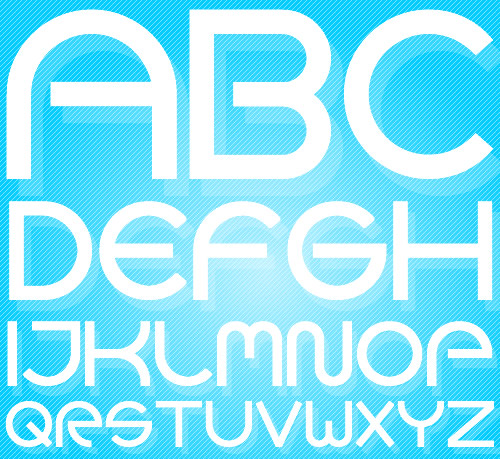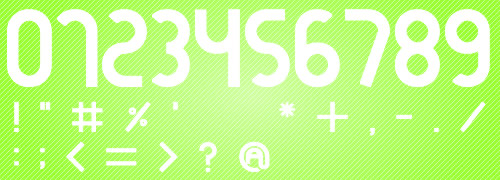
Font Design: Goca Logotype Beta
Il Font Design di oggi è: Goca Logotype Beta (download)
Questo carattere offre la possibilità di scrivere soltanto in maiuscolo, ideale per loghi e brochure.